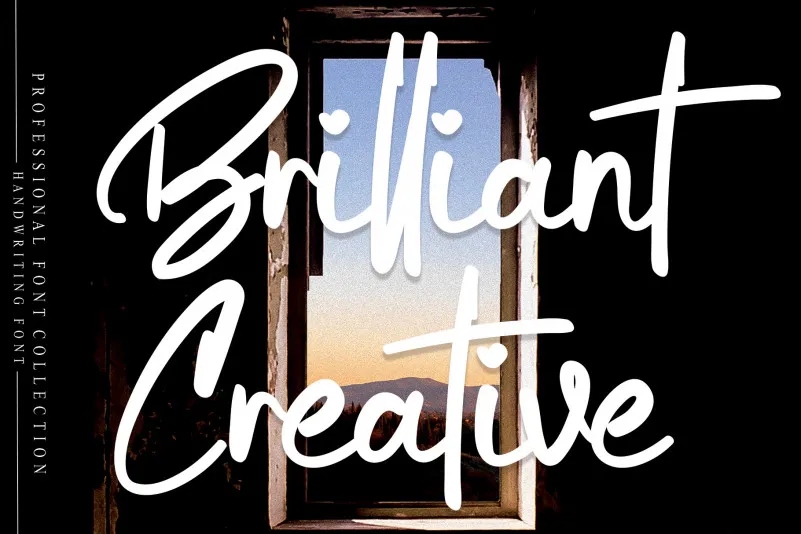
Brilliant Creative Script Font – Download Grátis
Aqui está uma descrição envolvente e natural para a página de download da fonte ‘Brilliant Creative Script Font’: Se você é amante dos grafismos criativos, então a fonte ‘Brilliant Creative Script Font’ foi feita para você. Ela traz um toque único e especial ao seu design gráfico, proporcionando uma experiência única em cada palavra escrita com ela. Esta fonte é ideal tanto para aqueles que querem personalizar as suas criações de formas inovadoras quanto para designers que desejam uma maneira única de expressar a sua criatividade. Com traços finos e detalhes elaborados, você terá acesso a um arsenal infalível de recursos gráficos. Essa fonte foi projetada por CreativeLetter, dedicado profissional com vasto conhecimento em criar soluções únicas para as necessidades do design gráfico contemporâneo. Numa era cada vez mais digitizada e visualmente intensificada, a ‘Brilliant Creative Script Font’ oferece um toque de modernidade e personalização que pode se adaptar ao seu projeto sem deixá-lo perder o seu sabor pessoal ou autêntico. Navegar pela ‘Brilliant Creative Script Font’, você encontrará uma grande variedade de recursos, desde tamanhos variados até configurações de cores, proporcionando-lhe a flexibilidade e liberdade necessárias para criar design exclusivo que reflete sua individualidade.